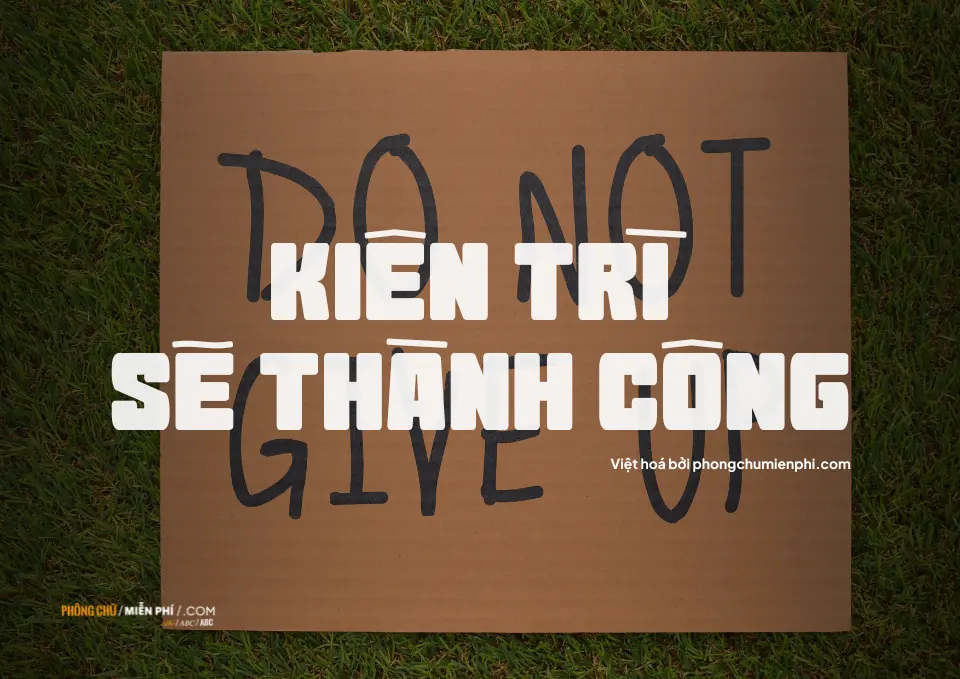
PCMP Gomarice Goma Block (tác giả: Gomarice / Goma Shin)
“Goma Block” là một font chữ in đậm, dạng khối được thiết kế bởi Goma Shin (còn được biết đến với tên Gomarice).
Nhà thiết kế: Goma Shin, nhà thiết kế font người Nhật (Fukuoka). Ông đã tạo ra nhiều font chữ độc đáo, trong đó có Goma Block.
Năm phát hành: Khoảng 2015.
Phong cách:
Font chữ to, dày, dạng poster, các nét bo tròn hoặc hơi tròn ở góc.
Được mô tả với các từ khóa: đậm, khối, poster, dễ thương, pop, robot.